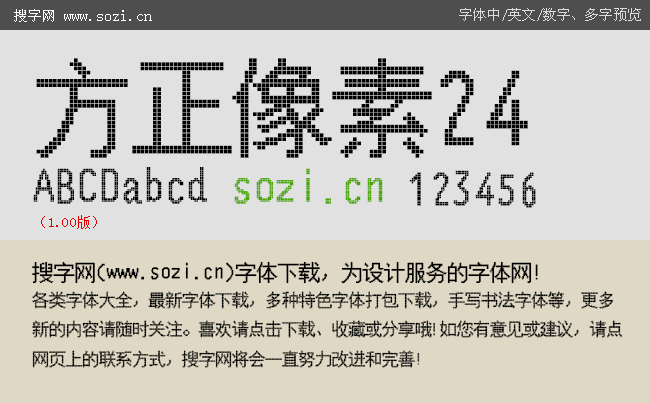
方正像素24
搜字網(wǎng)提供一款方正像素24字體中文字體下載,方正像素字體由正方形像素點(diǎn)組成的基于黑體、宋體基本字形的一套字體系列。方正像素體具有規(guī)范、工整,容易辨認(rèn)的特點(diǎn),適用于LED屏等電子屏幕,在易識的同時,體現(xiàn)科技感和現(xiàn)代感。適合書籍設(shè)計(jì)、展板設(shè)計(jì)、海報設(shè)計(jì)等廣告設(shè)計(jì)場合使用。